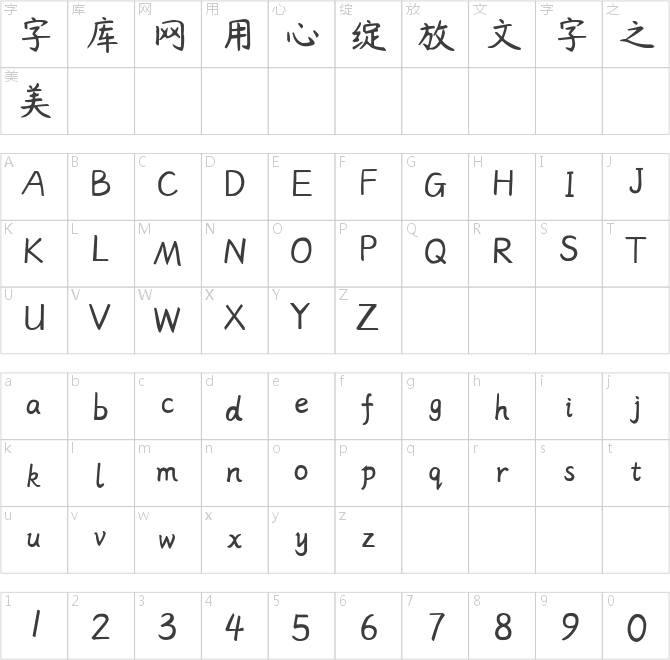
杨任东竹石体-Medium 详情页
字体名称: 杨任东竹石体-
杨任东竹石体-Medium
杨任东竹石体-Medium介绍
杨任东竹石体-Medium字体字库是一款让人赏心悦目、百看不厌的中文字体,适合各类广告和产品包装设计应用,字体大小3.98MB,格式为ttf字体,上传用户是赵家玉,作者/版权方为杨任东